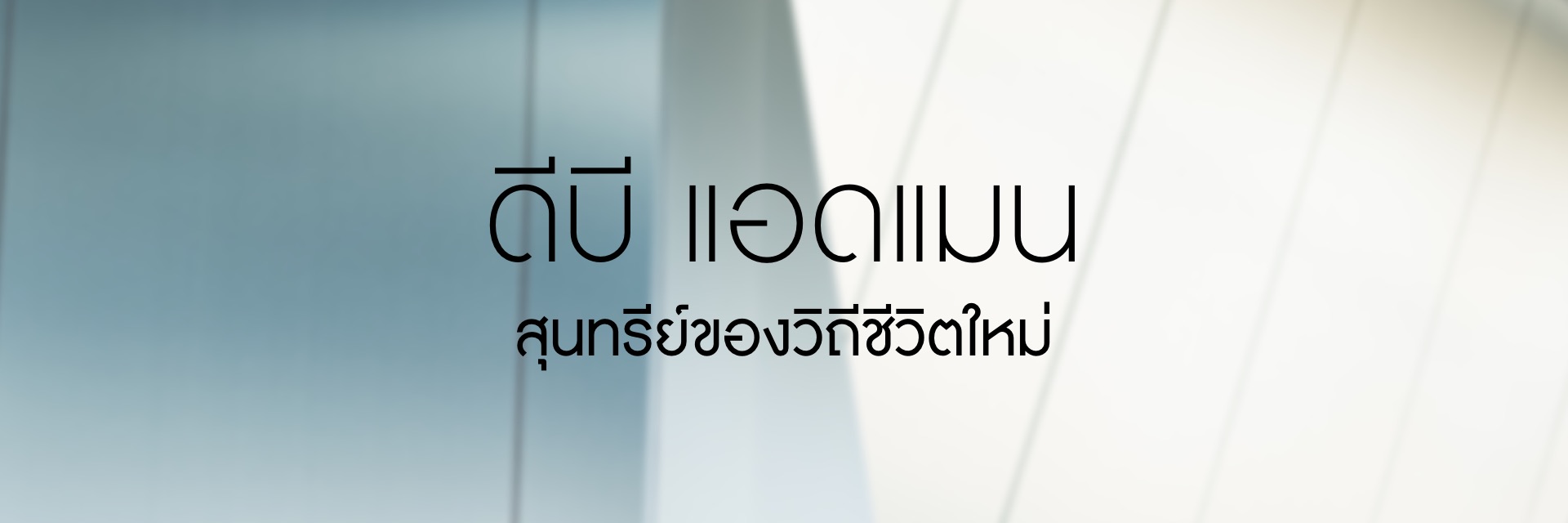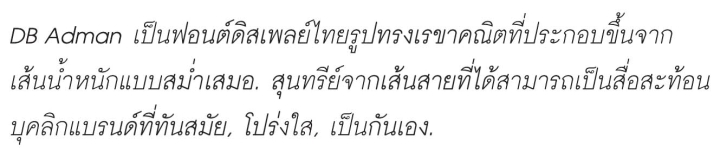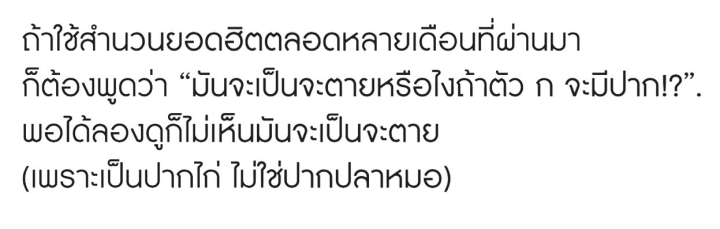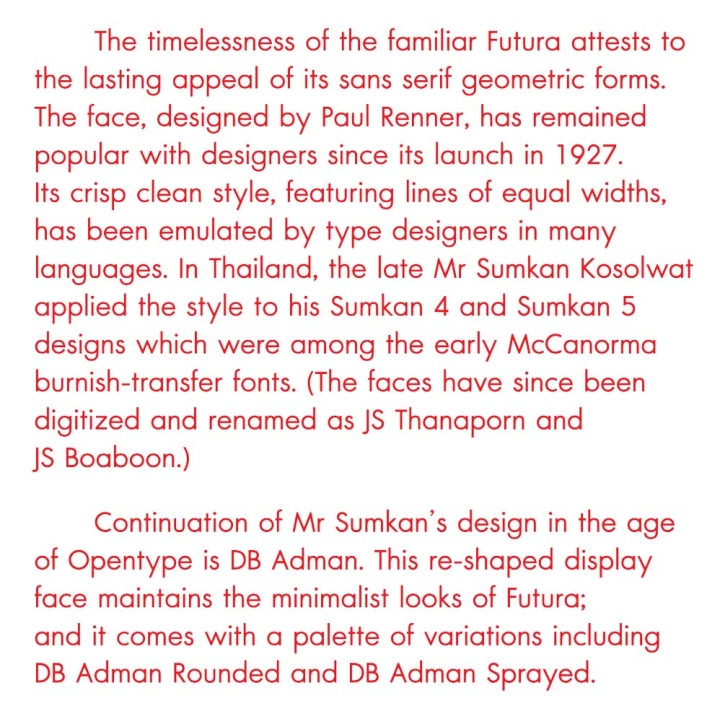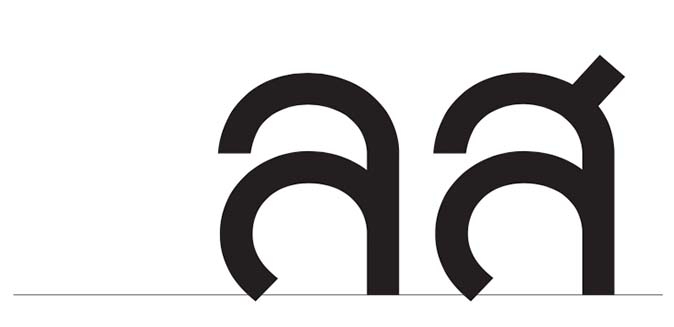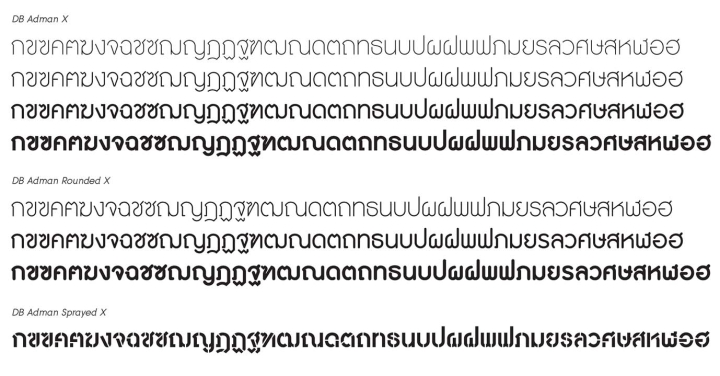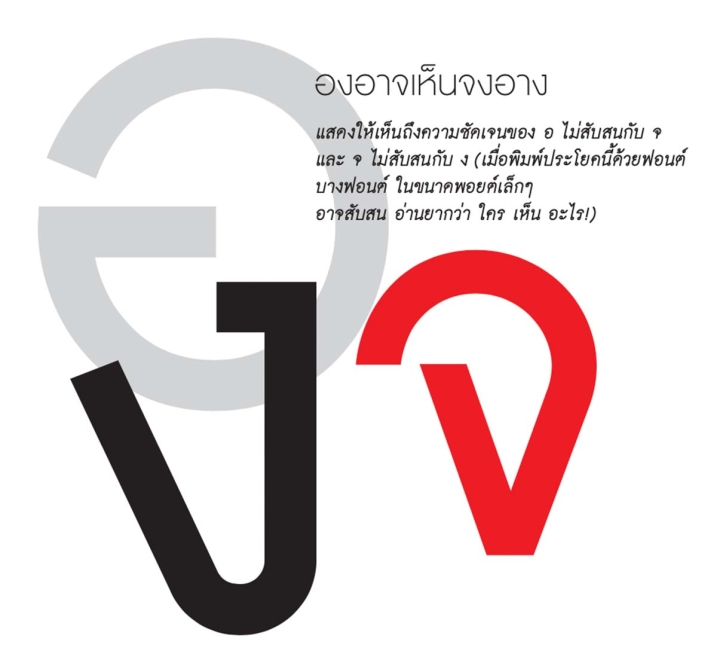
เมื่อโลกตะวันตกก้าวสู่ยุคอุตสาหกรรม มีตัวพิมพ์แหวกแนวชุดหนึ่งถือกําเนิดขึ้นโดยฝีมือ Paul Renner ผู้เป็นทั้งนักออกแบบหนังสือและนักเขียน, หน้าตาของตัวพิมพ์ชุดนั้น ดูราวกับเกิดขึ้นจากเครื่องมือเครื่องจักรแห่งอารยธรรม มากกว่าจากน้ํามือมนุษย์ธรรมดาผ่านอุปกรณ์สามัญ เช่น สิ่ว ค้อน, ปากกาคอแร้ง ฯลฯ. รูปลักษณ์อักษรโรมันแบบเดิมๆ ถูกจัดระเบียบใหม่ให้อยู่ในรูปทรงเรขาคณิต มันเป็นสิ่งประดิษฐ์ทางศิลปะที่ถูกใช้สื่อสารกับสังคมให้เปิดรับความเป็นจริงแห่งยุคสมัย ว่าโลกมันกําลังเปลี่ยนแปลงอย่างขนานใหญ่ ทั้งกระบวนการผลิต, วิถีชีวิต ตลอดไปจนถึงทัศนะใหม่ต่องานศิลปะ
Paul Renner เริ่มร่างแรกของ Futura ในปี ค.ศ. 1925 และเสร็จเป็นชุดสมบูรณ์ในปี ค.ศ. 1927 นับถึงตอนนี้ 80 กว่าปีแล้ว สุนทรีย์ของ Futura ก็ยังเป็นนิรันดร์, ตลอดเวลาราว 1 ชั่วอายุคนของ Futura ได้ส่งแรงกระเพื่อมต่อๆ ไปเป็นแรงบันดาลใจ นักออกแบบตัวพิมพ์ทั่วโลกทุกชาติภาษารวมทั้งไทย. หลักฐานสําคัญที่แสดงความจริงที่ว่านี้มีอย่างน้อย 2 ชิ้นด้วยกัน ชิ้นแรกคือแบบตัวอักษรลอก สําคัญ 4 (เส้นบาง) และ สําคัญ 5 (เส้น หนา) โดย สําคัญ โกศัลวัฒน์, ชิ้นที่สองคือ DB Erawan ที่ผมออกแบบให้เข้ากันกับ Futura ExtraBold. สําคัญ 4 และสําคัญ 5 ซึ่งดูจะเป็นแบบอักษรที่ใกล้เคียง Futura ที่สุดนั้น ในเวลาต่อมาได้รับการอนุรักษ์ไว้เป็น PostScript Font ในชื่อ JS Thanaporn และ JS Boaboon ตามลําดับ. น่าเสียดายที่ความประณีตบรรจงยังไม่สามารถเทียบเคียงได้กับต้นฉบับจริง, อย่างไรก็ตาม JS Thanaporn ยังได้รับความนิยมมาจนถึงทุกวันนี้ เป็นเพราะดูโปร่งอ่านง่าย ส่วน DB Erawan ก็เช่นกัน นอกจากจะดูกลมเกลี้ยงอย่าง Futura แล้ว ยังคงเป็นฟอนต์ที่แม้จะหนาอย่างที่สุด แล้วก็ยังอ่านง่ายอยู่ จึงคงนิยมใช้กันต่อๆ มา
แม้ว่า DB Erawan จะถูกปรับปรุงเข้ารหัสแบบ Unicode เรียบร้อยแล้วในปี พ.ศ.2549 ก็ยังคงมีเพียงน้ําหนักเดียว จึงยัง ไม่มีฟอนต์ไทยเสมือน Futura ที่มีครอบครัวใหญ่พอจะจัดเป็นมาตรฐานได้, ช่องว่างที่ผมสังเกตเห็นนี้ในที่สุดได้ถูกเติมเต็ม ด้วยฟอนต์ DB Adman.
ในการออกแบบ DB Adman ผมมิได้เคร่งครัดกับความเป็น Futura จนเกินไป มีการเปิดช่องว่างไว้เพื่อปรุงแต่งสิ่งใหม่เข้าไปบ้าง. ทําไปทํามาแม้แต่ Futura เดิมเองก็ยังถูกปรับปรุงสัดส่วนให้เข้ากับตัวไทยที่เสร็จแล้ว ดังจะได้กล่าวในตอนท้าย
นอกจากจะต้องยึดรูปทรงเรขาคณิตแบบ Futura เป็นตุ๊กตาแล้ว สิ่งที่ผมคํานึงถึงอยู่เสมอก็คือเรื่องการอ่าน, ผมเชื่อว่าตัว เสมือนหรือตัวเฉียดๆ Futura ที่จะเกิดขึ้น อย่างไรเสียก็เป็นตัวพิมพ์ที่เหมาะจะใช้ในการพาดหัวในขนาดโตพอประมาณ. ถ้าจะใช้เป็นตัวเกริ่นนําหรือตัวโปรยในปริมาณไม่มากก็ย่อมอนุโลมได้ แต่ไม่ควรใช้ในขนาดที่เล็กจนเกินไป. จึงน่าจะเป็นการดีถ้าการ ออกแบบ DB Adman จะได้คํานึงถึงตัวเนื้อรูปทรงเรขาคณิตไว้บ้าง, ตัวเนื้อที่เหมาะสมจะใช้ร่วมกันในกรณีงานโฆษณาที่ต้องลง เนื้อหารายละเอียดค่อนข้างมาก หรือกรณีออกแบบหนังสือพิมพ์ นิตยสาร รายงานประจําปี ไปจนถึงแผ่นพับ ฯลฯ. ด้วยวิธีคิดแบบนี้ผมจึงให้ความสนใจไปที่ DB FongNam ตัวเนื้อที่กลมกลืน กับ Avant Garde ญาติของ Futura มากกว่า DB Erawan ตัว ดิสเพลย์ที่เป็นเงาอย่างหนาของ Futura โดยตรง
ระหว่างลงมือร่างผมจึงตั้งคําถามกับตัวเองว่า ทําไม Futura ภาคภาษาไทย ถึงต้องมีตัว ก เป็นรูป U คว่ำเกลี้ยงๆ แบบ Sumkan 4 หรือ DB Erawan? ถ้าใช้สํานวนยอดฮิตตลอดหลายเดือนที่ผ่านมาก็ต้องพูดว่า "มันจะเป็นจะตายหรือไง ถ้าตัว ก จะมีปาก! ?" พอได้ลองดูก็ไม่เห็นมันจะเป็นจะตาย (เพราะเป็นปากไก่ ไม่ใช่ปากปลาหมอ) ผมร่างตัว ก และอักษร คล้าย ก ทุกตัว (ถ, ภ, ฌ ญ ฎ ฏ ณ ฯลฯ) ให้มีปากเป็นเส้นทะแยงมุมไปรับเส้นโค้งบนเหมือน ก ของ DB FongNam, ตัว ถ ที่มีปากชัดเจนแบบนี้ช่วยให้มันดูไม่สับสนว่าเป็นตัว ด (เหมือน ถ, ด ของ Sumkan 4 ซึ่งอาจดูสับสนกันได้)
แผ่นอักษรลอก สำคัญ 4 และ สำคัญ 5 (ขนาดตัวสูง 5 มม.) ตัว ด อาจดูสับสนเป็น ถ ได้ เพราะคล้าย ก เติมหัว และ ถ ดูคล้าย ด มาก อาจสับสนเมืื่อเป็นฟอนต์ JS Thanaporn ที่ใช้ในขนาดเล็กกว่า 5 มม.
• ง, จ แทนที่จะเหมือนของ DB Erawan ผมกลับเลือกเอาของ DB FongNam มา. ผลคือทําให้ตัว ง. จ. อ ของ Adman แยกแยะออกจากกันอย่างเด่นชัด และเพราะ 3 ตัวนี้มี ความถี่ในการใช้งานสูง จึงช่วยให้ภาพรวมของข้อความที่พิมพ์ขึ้นมาด้วยฟอนต์นี้อ่านง่าย. โดยสรุปแล้วการที่ผมเลือกเอาตัว ก, ง. จ ของ DB FongNam มาปัดฝุ่นใช้ใหม่ เสมือนเป็นการยิงปืนนัดเดียวได้นก 2 ตัว คือได้ทั้ง DB FongNam มาเข้าก๊วนเป็นตัวเนื้อ แถมยังได้แก้ปัญหาคู่สับสนมีผลให้อ่านง่ายขึ้น
• ผ, ฝ มีหัวที่โค้งเข้าตัวตามเข็มนาฬิกา (จากเลข 9 ถึง 12) ทําให้ ดูไม่สับสนกับตัว พ, ฟ.
• ข มีจุดเด่นคือลักษณะขมวดม้วนต่อเนื่องกับเส้นหน้าเป็นรูป S-curve (กลับด้าน) เป็นการเชื่อมต่อของวงกลม 2 วงโดยไม่มีการสะดุด
• ย การเพิ่มรอยหยักด้วยเส้นทะแยงสั้นๆ เข้าออก ทําให้สามารถมาบรรจบกันกับเส้นล่างที่กลมเกลี้ยงแบบฐานตัว บ ได้
• ล ถ้าสังเกตให้ดีจะเห็นว่า จากหัวที่โค้งเข้าหาเส้นหลังล้วน มีรัศมีความโค้งใกล้เคียงกัน ล้อกับรัศมีความโค้งของเส้น บนพอดี, เคล็ดลับที่ทําเช่นนี้ได้ (โดยยังคงสามารถรักษา สัดส่วนให้สัมพันธ์กับรูปอักษรอื่นๆ ทั้งชุดได้นั้น) อยู่ที่การ ตัดปลายหัว ในแนวทะแยงเข้าหาจุดศูนย์กลางความโค้ง ทั้งนี้มีการแก้ดวงตาโดยปล่อยให้ส่วนล่างสุดของหัวเลยตำ่ลงไปจากเส้นฐาน (baseline) เล็กน้อย
เมื่อรวมกันเข้ากับการเก็บรายละเอียดเล็กๆ น้อยๆ เช่น หัวไม้โทแบบเลข 2 ที่ตัดปลายหัวในแนวทะแยง หรือการันต์ รูปตัว J ฯลฯ ช่วยทําให้ DB Adman กลายเป็นตัวแทนสุนทรีย์ของวิถีชีวิตใหม่ที่มีเอกลักษณ์, ชุดอักษรโรมันของ Futura มีช่วง ascender ยาวขึ้นไปเท่าความสูงตัวตามทําให้ดูค่อนข้างรุ่มร่าม ไปสําหรับตัวอักษรไทยใน DB Adman. ความสูงของตัวอักษรนําของ Futura เดิมมากเป็น 2 เท่าของตัวอักษรตาม ถ้าเรานําสัดส่วนเดิมๆ มาย่อเพื่อให้ตัวเลข (ซึ่งสูงเท่าตัวอักษรนํา) ดูเหมาะสมกับความสูงตัวพยัญชนะไทย เราจะได้ตัวอักษรตามที่เล็กเกินไป. ปัญหาทั้งหมดที่พบใน Futura ได้รับการแก้ไข รวมไปจนถึงปลายตัวอักษรโรมันเดิมที่แหลมจัด (เช่น A, N) ที่ดูไม่ค่อยเข้ากับชุดภาษาไทย ก็ถูกเฉือนทิ้งไปเล็กน้อยไม่ให้เป็นที่สังเกตเห็นได้ชัด
DB Adman ทั้ง 4 น้ําหนักคือ UltraLight, Light, Regular, Bold ถูกนําไปเติมเส้นตรงในแนวตั้งและตั้งชื่อใหม่ให้สอดคล้อง ว่า DB BrandVoice (วิธีนี้ยังคงรักษาความกลมไว้ได้ ต่างจาก Futura Condensed ที่ตัว O จะดูเป็นวงรี), DB Adman จากน้ําหนัก Light ขึ้นไปถูกนําไปตกแต่งปลายให้มน เป็น DB Adman Rounded. ไม่เพียงเท่านั้น ยังมี DB Adman Sprayed ที่ตัดแต่ง จาก DB Adman Bold เพิ่มขึ้นมาให้นักออกแบบได้ใช้อย่างจุใจ แต่ถึงอย่างไรก็ไม่สามารถใช้ครอบครัว Adman ร่วมกันไปแบบครอบจักรวาลได้ ถ้าจะใช้ตัวเล็กๆ 14-18 พอยต์เป็น text ให้อ่านนานๆ ควรเปลี่ยนไปใช้บริการของ DB FongNam. (ดูตัวอย่าง ได้จาก Mag Ad. ของ รมย์รวินท์คลินิก, นิตยสารบ้านและสวน Center Point, และ a font a month ที่คุณกําลังอ่านอยู่นี้)
ในทางกลับกัน ใครก็ตามที่เป็นแฟนพันธุ์แท้ของ DB FongNam, DB Soda, หรือฟอนต์ตัวเนื้อค่ายอื่นๆ ที่มีรูปทรง เรขาคณิตเหมือนๆ กันก็ตาม, การมี DB Adman รวมทั้ง DB BrandVoice ใช้ร่วมกันให้ครบเครื่อง น่าจะเป็นการช่วยส่งสําเนียงของแบรนด์ออกมาอย่างมีสุนทรีย์... สุนทรีย์ของวิถีชีวิตใหม่ ที่สร้างจากเครื่องมือแห่งอารยธรรมใหม่ที่ชื่อว่า FontLab
ไม่ใช่จากน้ํามือมนุษย์ธรรมดาอย่างผม.